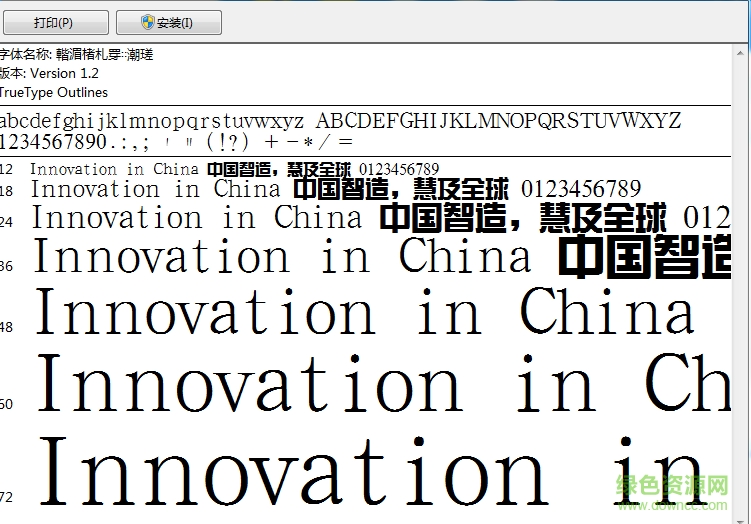
該字體與方正尚酷黑、方正譚黑、造字工房力黑及蒙納超剛黑相似,由數(shù)十位設(shè)計(jì)師共同創(chuàng)作,透過字體傳達(dá)出銳氣、進(jìn)取與力量,具有良好的觀賞性與設(shè)計(jì)感,可以廣泛應(yīng)用于廣告設(shè)計(jì)、宣傳海報(bào)、ppt、影視制作以及任何使用文字的領(lǐng)域!